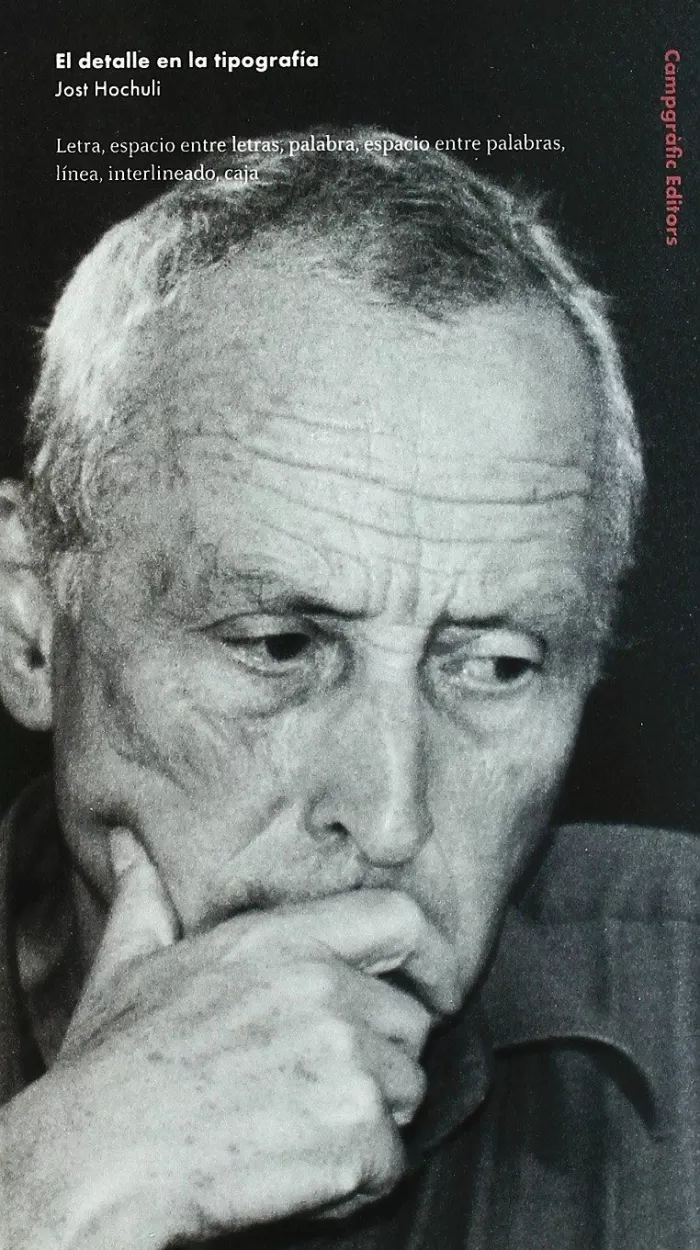
EL DETALLE EN LA TIPOGRAFÍA
LETRA ESPACIO ENTRE LETRAS PALABRA ESPACIO ENTRE PALABRAS LINEA
HOCHULÍ, JOST
EL DETALLE EN LA TIPOGRAFÍA
CAMPGRÀFIC EDITORS
2007
Una introducción clara a aquellas cuestiones que conciernen a la legibilidad y compresión de los textos y la importancia de la tipografía. El detalle en la tipografía constituye una introducción concisa y sucinta a todas aquellas cuestiones que conciernen a los caracteres, las lineas y los parrafos, así como a todos aquellos elementos que resultan imprescindibles en la legibilidad de un texto impreso. Un diseño adecuado e interesante hará las delicias de lectores; cuando los detalles no son idóneos, la lectura resulta cansada. Quien desee que sus impresos no sean únicamente contemplados, sino también leidos, ha encontrado en este opúsculo una guia imprescindible. Apareció por primera vez en 1987, se ha traducido a seis idiomas y gozó de un éxito indiscutible en las zonas germánicas. Ahora vuelve en una edición completamente renovada y ampliada con numerosos ejemplos prácticos.
Una introducción clara a aquellas cuestiones que conciernen a la legibilidad y compresión de los textos y la importancia de la tipografía. El detalle en la tipografía constituye una introducción concisa y sucinta a todas aquellas cuestiones que conciernen a los caracteres, las lineas y los parrafos, así como a todos aquello s elementos que resultan imprescindibles en la legibilidad de un texto impreso. Un diseño adecuado e interesante hará las delicias de lectores cuando los detalles no son idóneos, la lectura resulta cansada. Quien desee que sus impresos no sean únicamente contemplados, sino también leidos, ha encontrado en este opúsculo una guia imprescindible. Apareció por primera vez en 1987, se ha traducido a seis idiomas y gozó de un éxito indiscutible en las zonas germánicas. Ahora vuelve en una edición completamente renovada y ampliada con numerosos ejemplos prácticos.